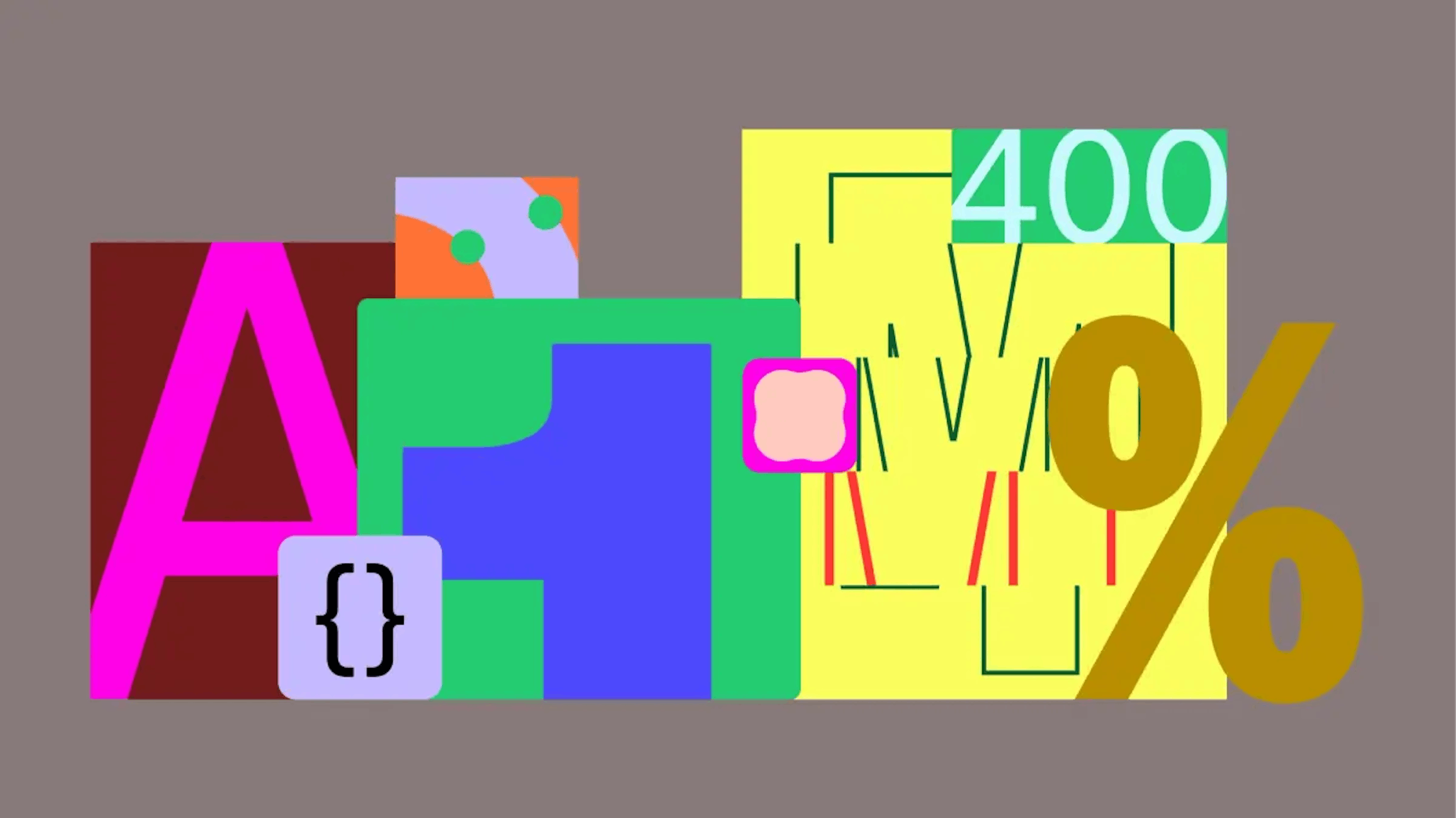
Figmaブランドを表現する新たなコーポレートフォント「Figma Sans」が登場
Figmaはブランドの価値提供をデザイナーからプロダクト開発全体へと拡大していく中で、そのブランドイメージの刷新にも取り組んできました。その中で、カラーパレットやイラストレーションスタイルの変更に加え、タイプファウンドリーGrilli Typeと協力し新たなカスタムフォント「Figma Sans」を開発したとのことです。
Grilli Typeのチームは、フォントをブランドビジュアルに適応させるために、多くのフィードバックを反映したとのこと。Figmaのブランドチームも、形状、ライン、パターン、色などの要素とフォントの進化を同時に探求。その結果、ブランドの新しいビジュアル要素との完璧なマッチングが実現したとのこと。
Figma Sansは、60種類の静的フォントと6種類の太さの5つのファミリーからなる書体となり、コンテキストが要求するあらゆるものに対応する光学サイズを提供できるように設計されています。大規模なスケールで使用されるディスプレイ体はブランドの個性を伝えることに重点を置いている一方、テキストスタイルは、より実用的な本文やUI上での使用に最適化されています。
Figmaはデザイナーだけでなく、プロダクトチーム全体を巻き込むプラットフォームとして成長しており、この新たなフォントはその象徴としてブランドを表現していくことになりそうです。